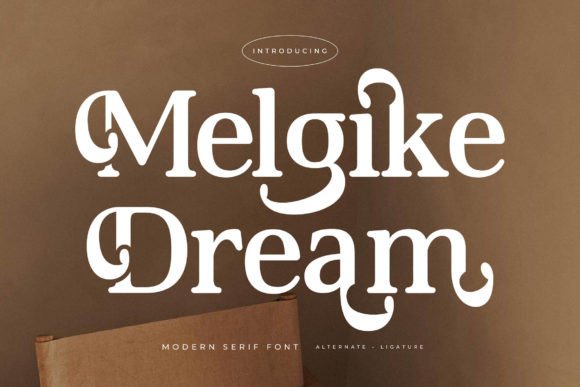
Melgike Dream
Doğru tasarım öğelerini bulmak zor olabilir, ancak Melgike Dream, çalışmanızı anında bir üst seviyeye taşıyan olağanüstü bir koleksiyon sunar.
İster İsteğe Bağlı Baskı (POD) ürünleri, ister düğün davetiyeleri veya sosyal medya grafikleri oluşturuyor olun, Melgike Dream ideal bir uyumdur.